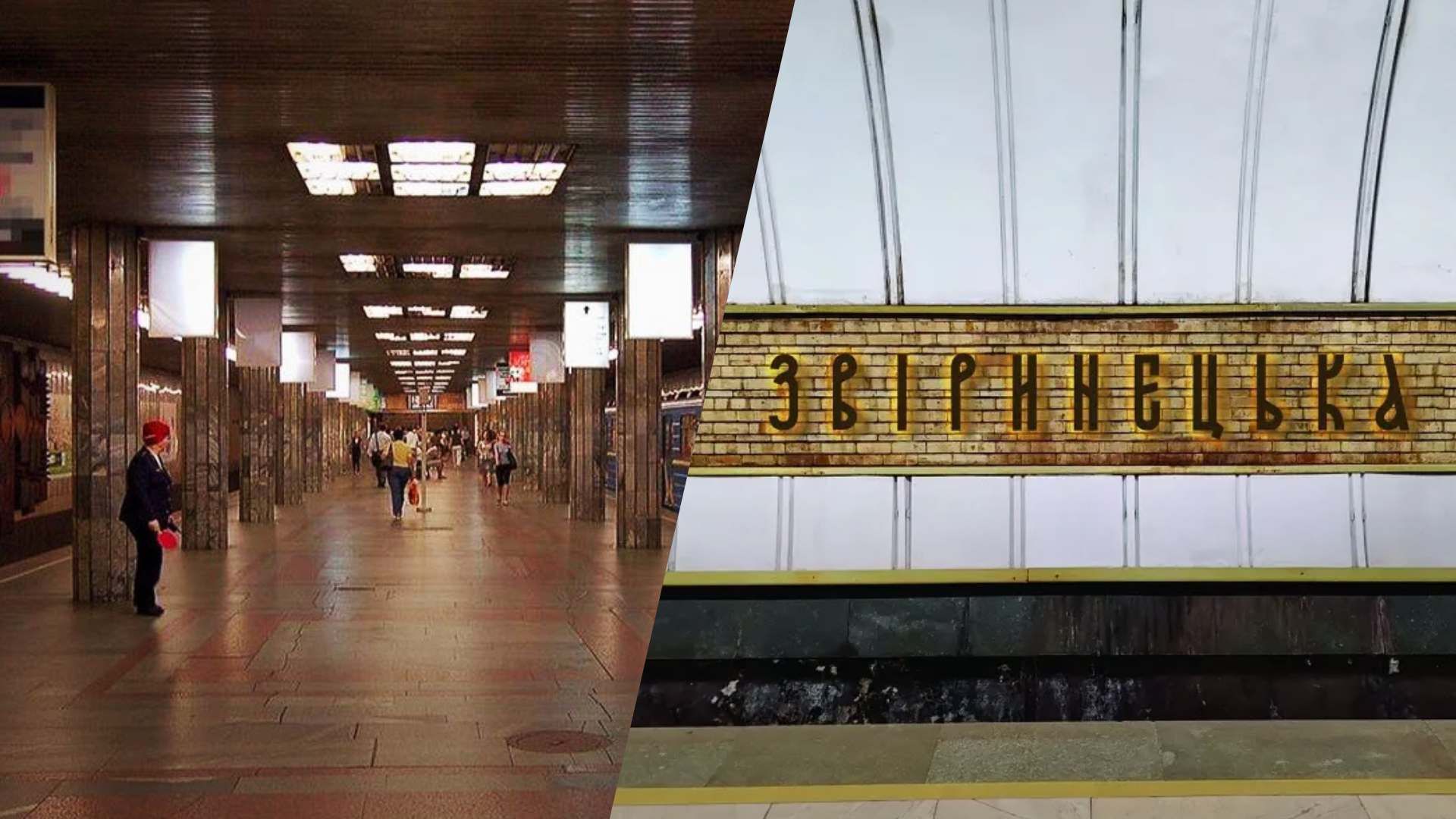
Дизайнер разработал шрифт станции метро / Коллаж 24 Канала
Графический дизайнер Богдан Гдаль представил вариант дизайна названия для переименованной станции метро "Дружбы народов". Накануне, 18 мая, название сменили на "Зверинецкую".
Гдаль написал, что он вдохновился буквами, которые для проекта разрушенных русскими церквей Киева готовил Саша Комьяхов. Поэтому для названия станции метро использовал такой же шрифт.
Конечно, чистой вязи здесь не получится, потому что она будет нечитаемой, но сами буквы интересны. Хотя, пока они не ощущаются как окончательный вариант
Что означает "Зверинецкая"
Название "Зверинецкая" происходит от исторической местности Киева между Печерском, Выдубичами, Теличкой и Черной Горой. Она известна еще от Киевской Руси. Предполагают, что это происходит от места охот киевских князей на дикого зверя.
К слову, Гдаль также создал шрифт для новой надписи на станции метро "Почайна". Он должен повторять тот, что на станции "Печерская".